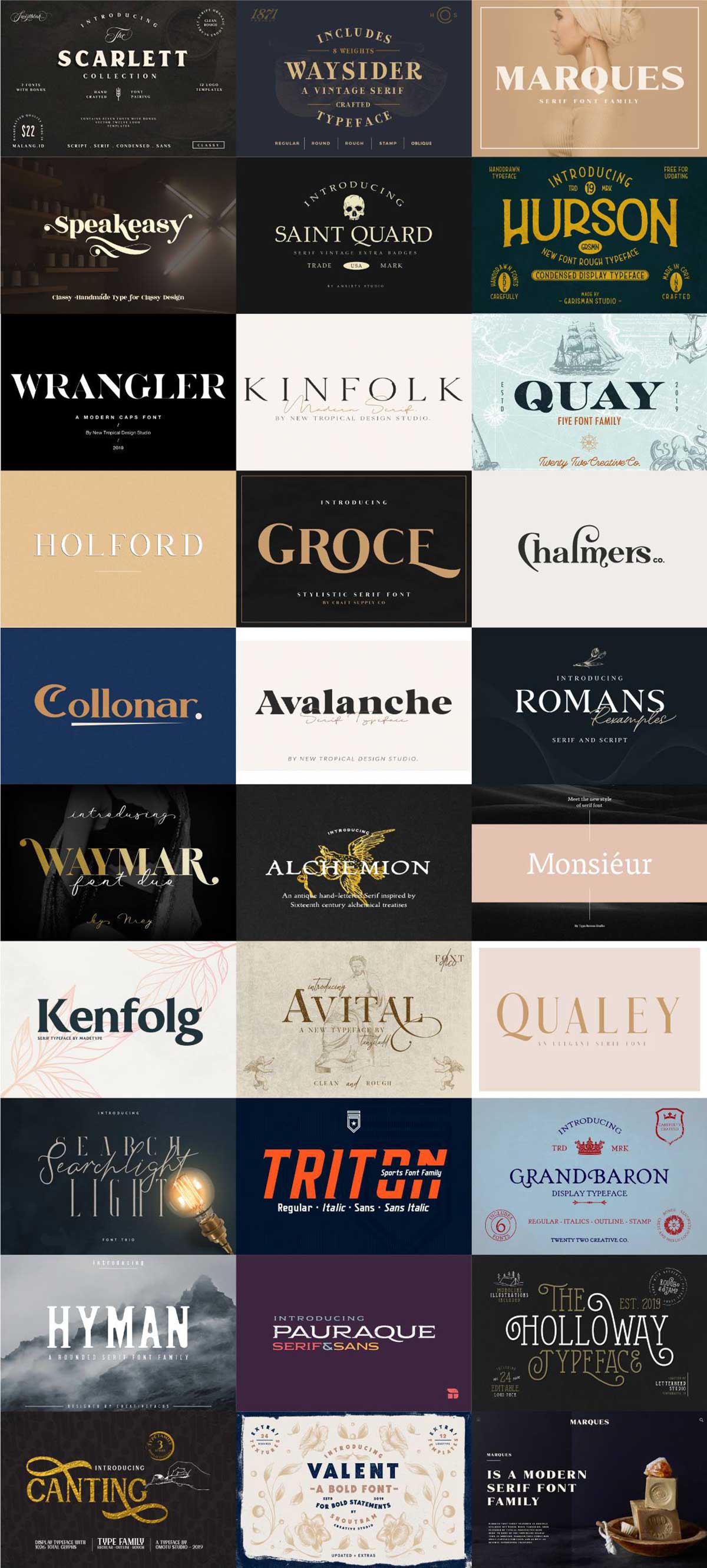
Pixel Surplusでは、今年の4月に販売して大好評だったモダンセリフ書体29セットを収録したフォント集「The Modern Serif Font Bundle(ザ・モダン・セリフ・フォント・バンドル)」が一ヶ月限定で再販売中です。
エレガントで洗練された雰囲気を演出するのに便利なセリフフォントを、まとめて手に入れるチャンス!前回買い逃した方はこの機会をお見逃しなく。
「The Modern Serif Font Bundle」の気になる中身
今回のバンドルの中で、私が特に気になるフォントはこちらです。
Kinfolk – New Tropical Design
大文字の「O」と「Q」のデザインがさりげなくユニークな「Kinfolk」。ほんの少しだけ遊び心のあるデザインが、おしゃれで大人っぽい印象です。さりげなく使って他の媒体と差をつけたいですね。
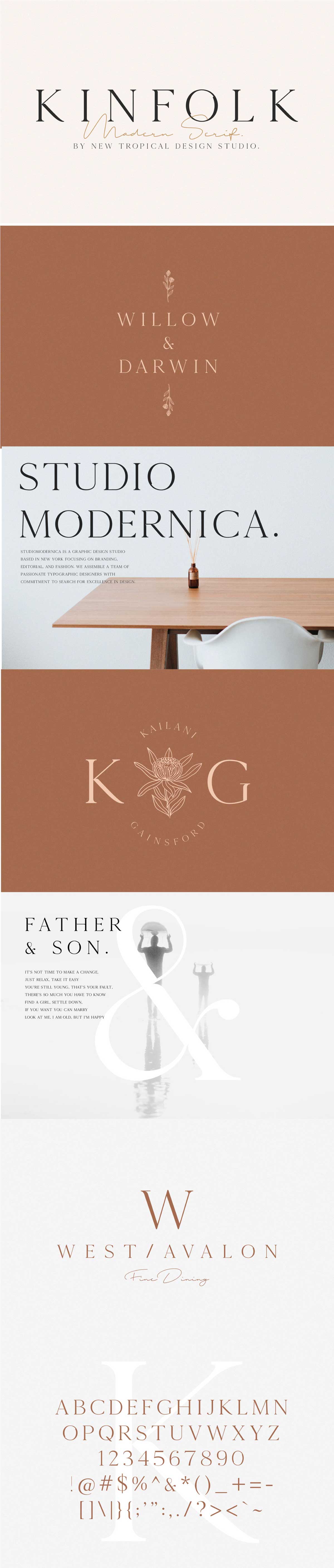
Avalanche – New Tropical Design
縦と横線のコントラストがはっきりしたセリフ書体「Avalanche」。手書き風フォントと組み合わせると、より今っぽくなります。思いきり大きく使って存在感をアピールしたい書体です。
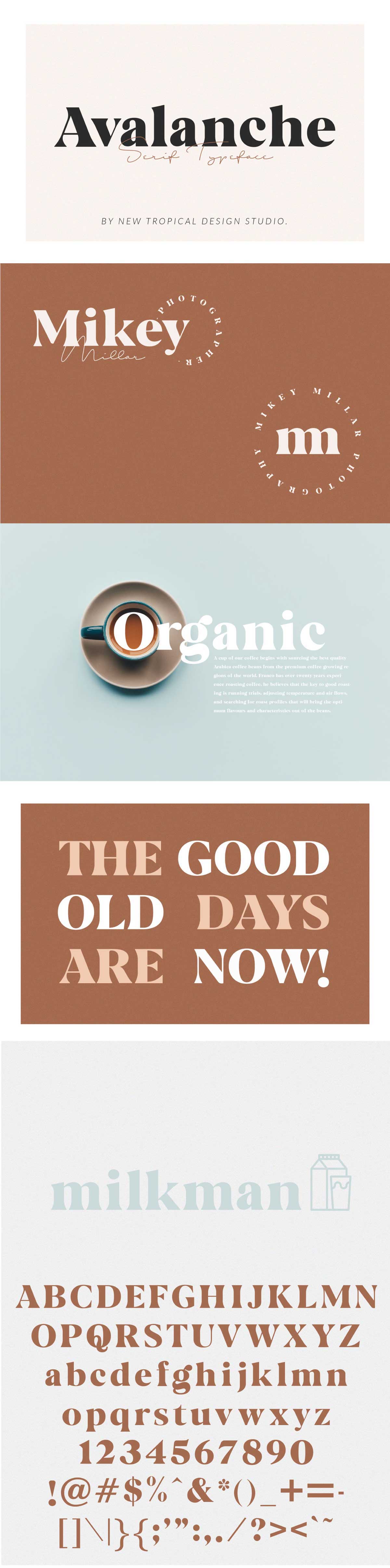
Holford – Pixel Surplus
Pixel Surplusオリジナルフォント「Holford」。シンプルで使いやすく、多言語に対応しています。このフォントだけ買っても16ドルするので、欲しいかたはバンドルで買った方が他のフォントも使えてお得ですよ。
Chalmers – Swistblnk Std.
飾り用の字体も用意された「Chalmers」を使えば、エレガントなロゴがパパッと作成できます。連字も豊富に用意されていて、簡単に美しいタイポグラフィが可能ですよ。
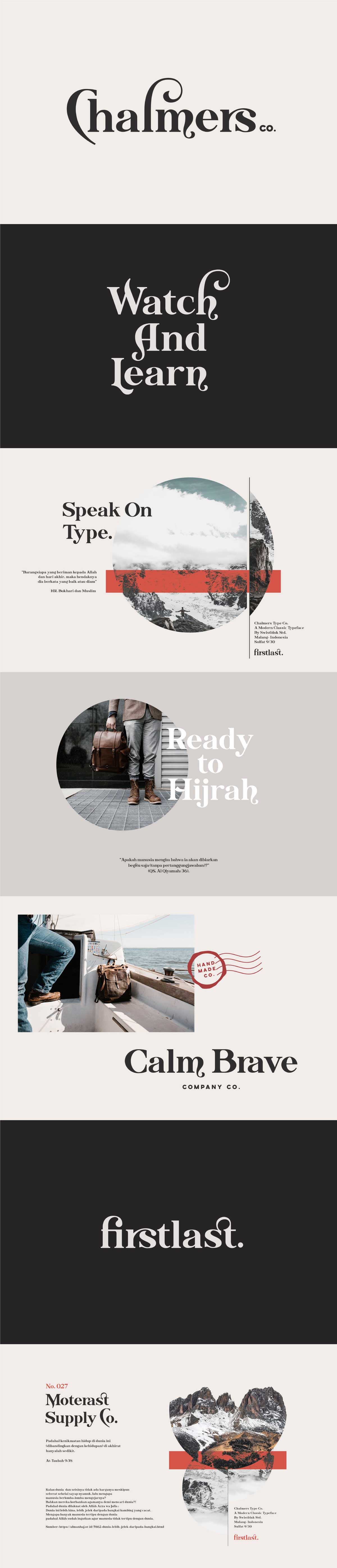
Triton – ANDR35
スポーツチームのロゴなど、男性向けの媒体にぴったりのフォント「Triton」。サンセリフ体も収録しており、デザインの幅が広がります。こういうフォントは一つ持っておくと何かと便利ですよ。
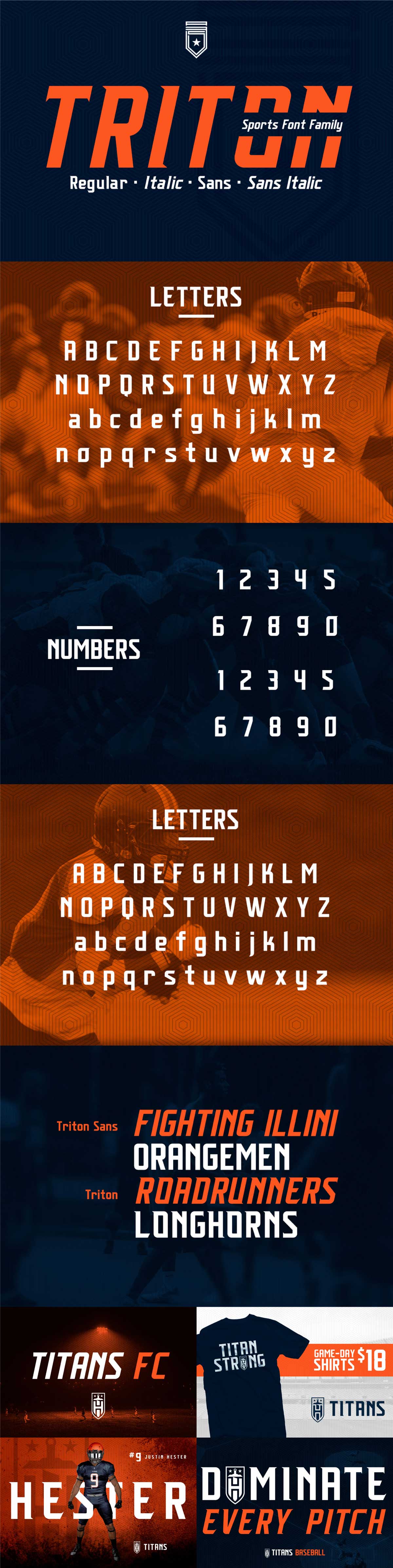
このほか今っぽいフォントばかり合計29書体セットを収録しています。この記事で紹介できなかった書体はぜひ詳細ページから確認してくださいね。